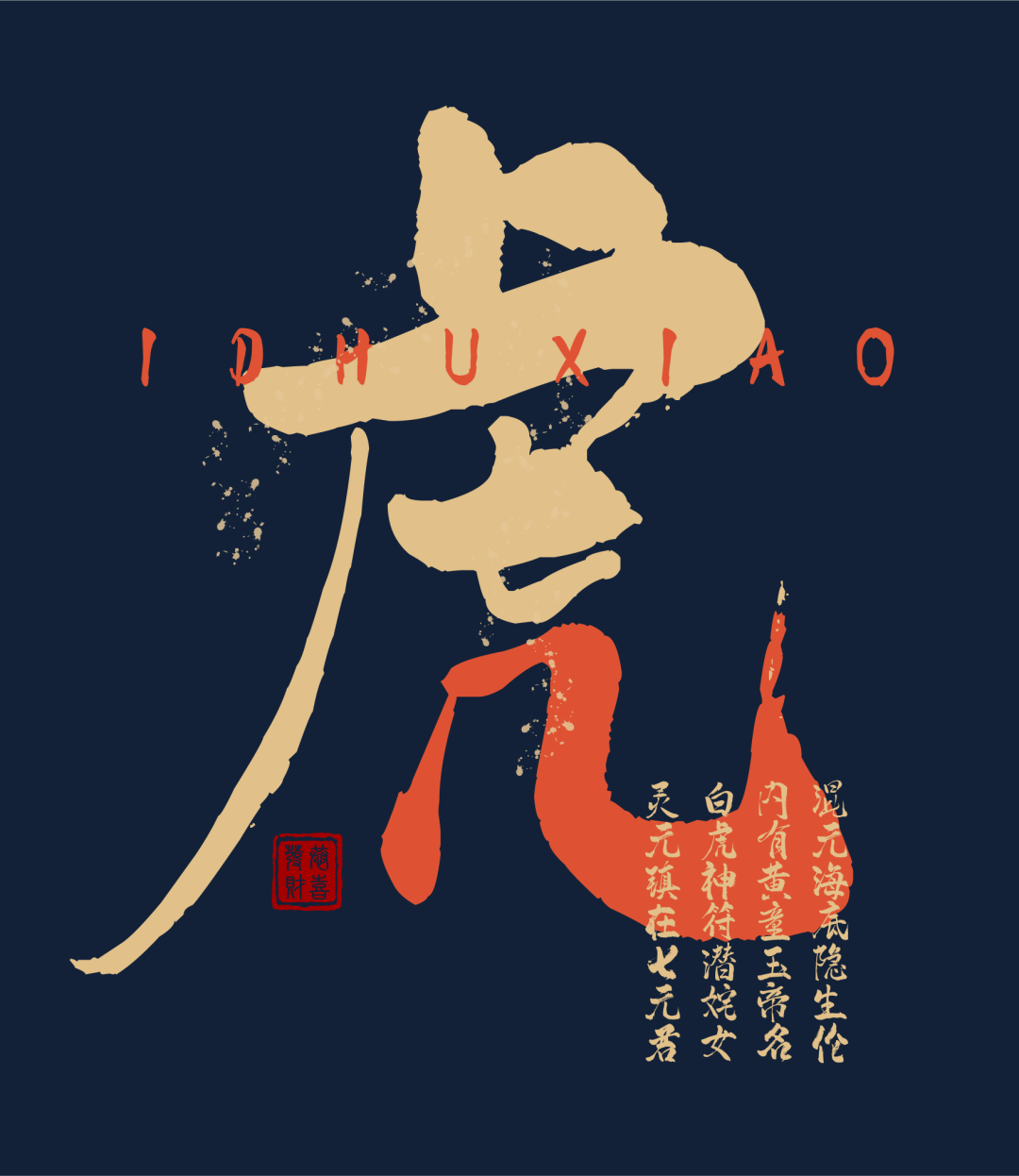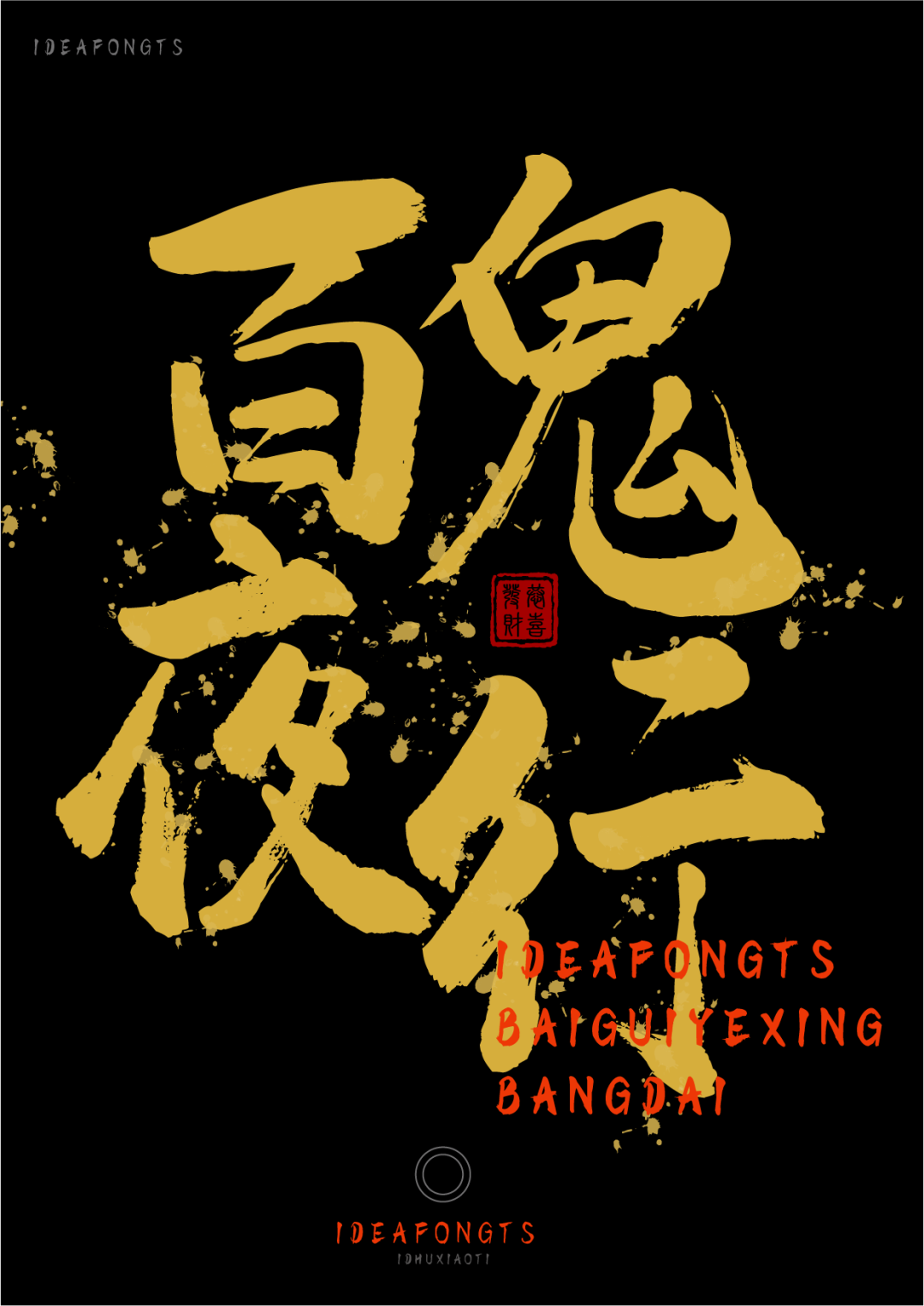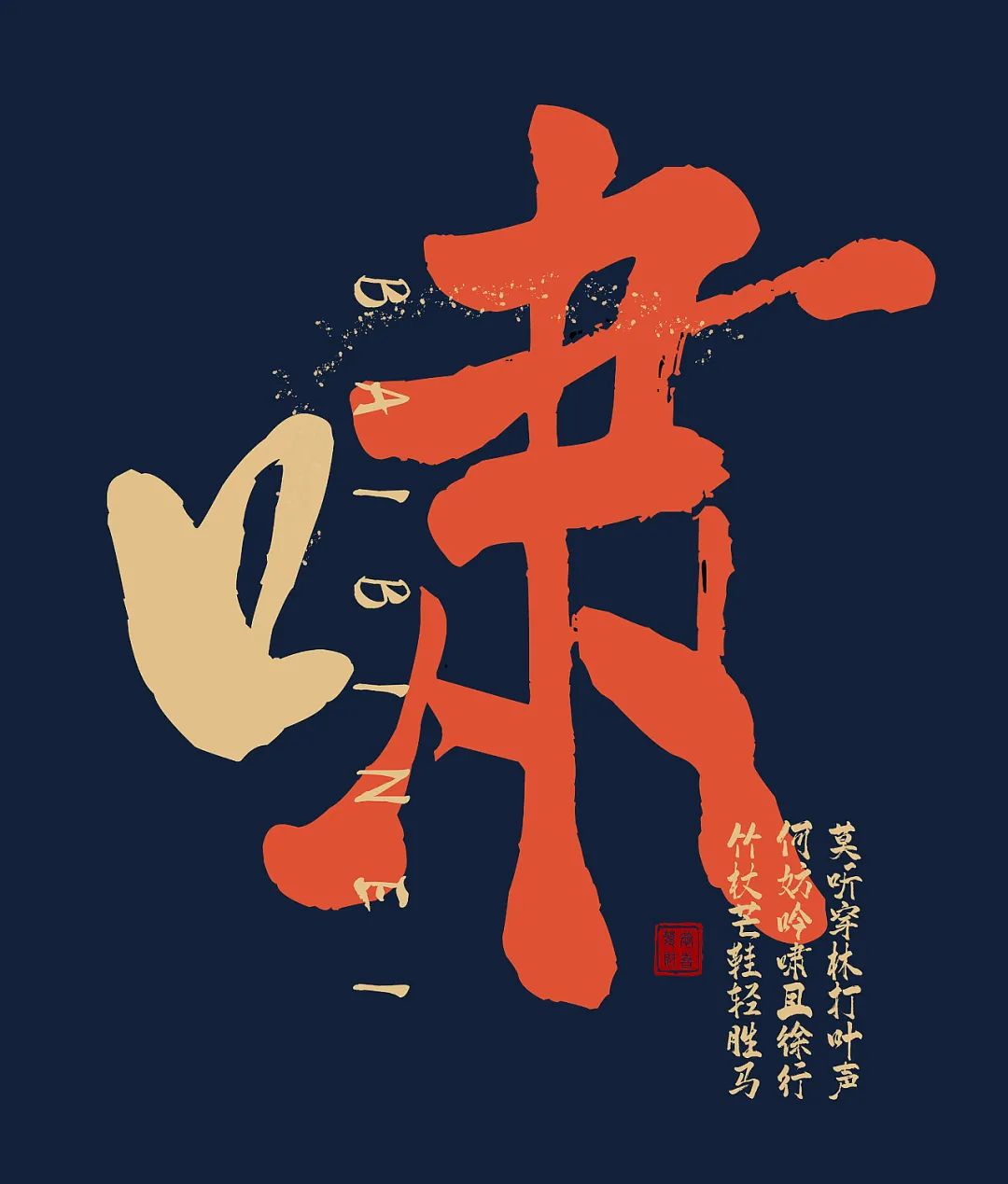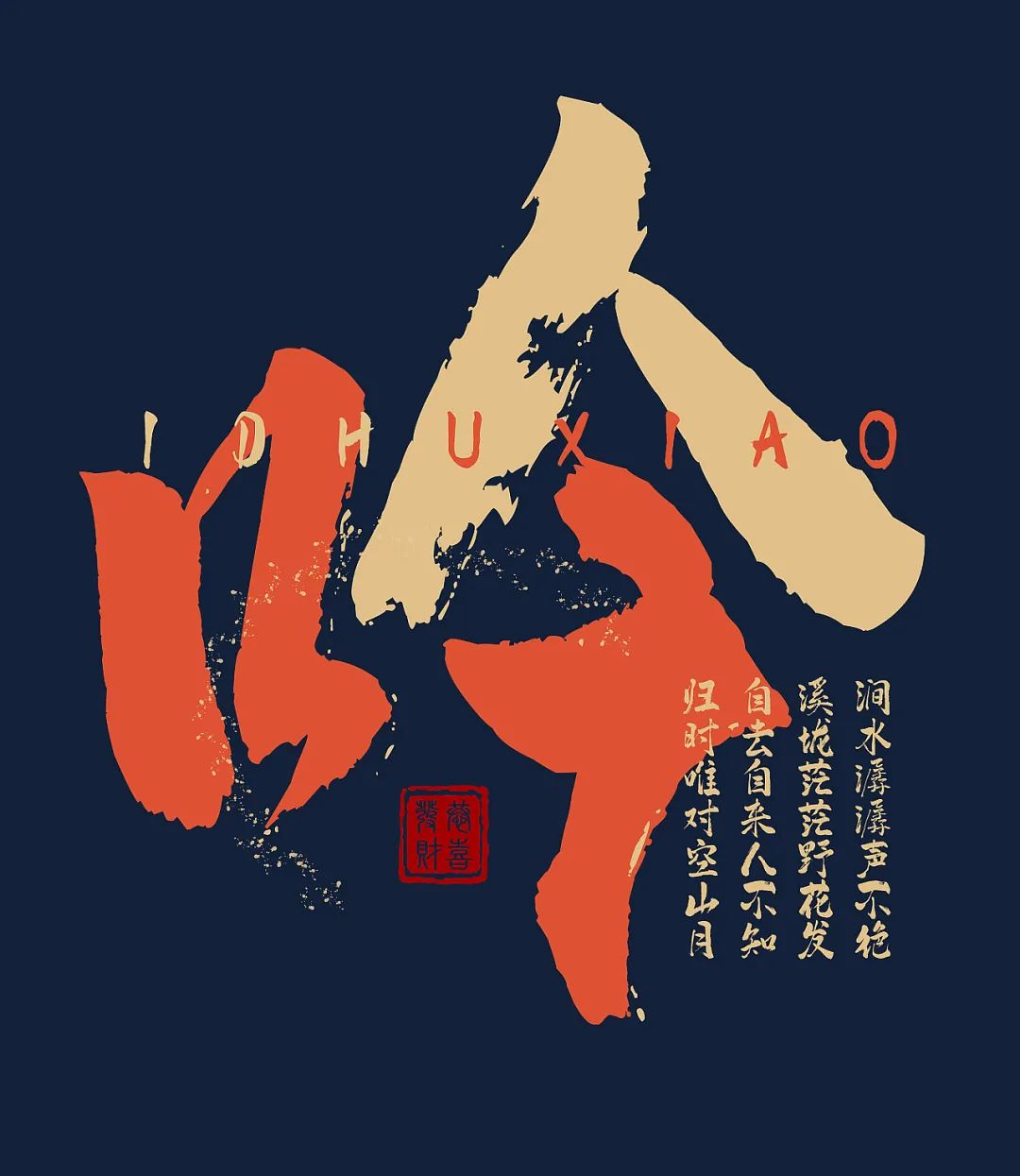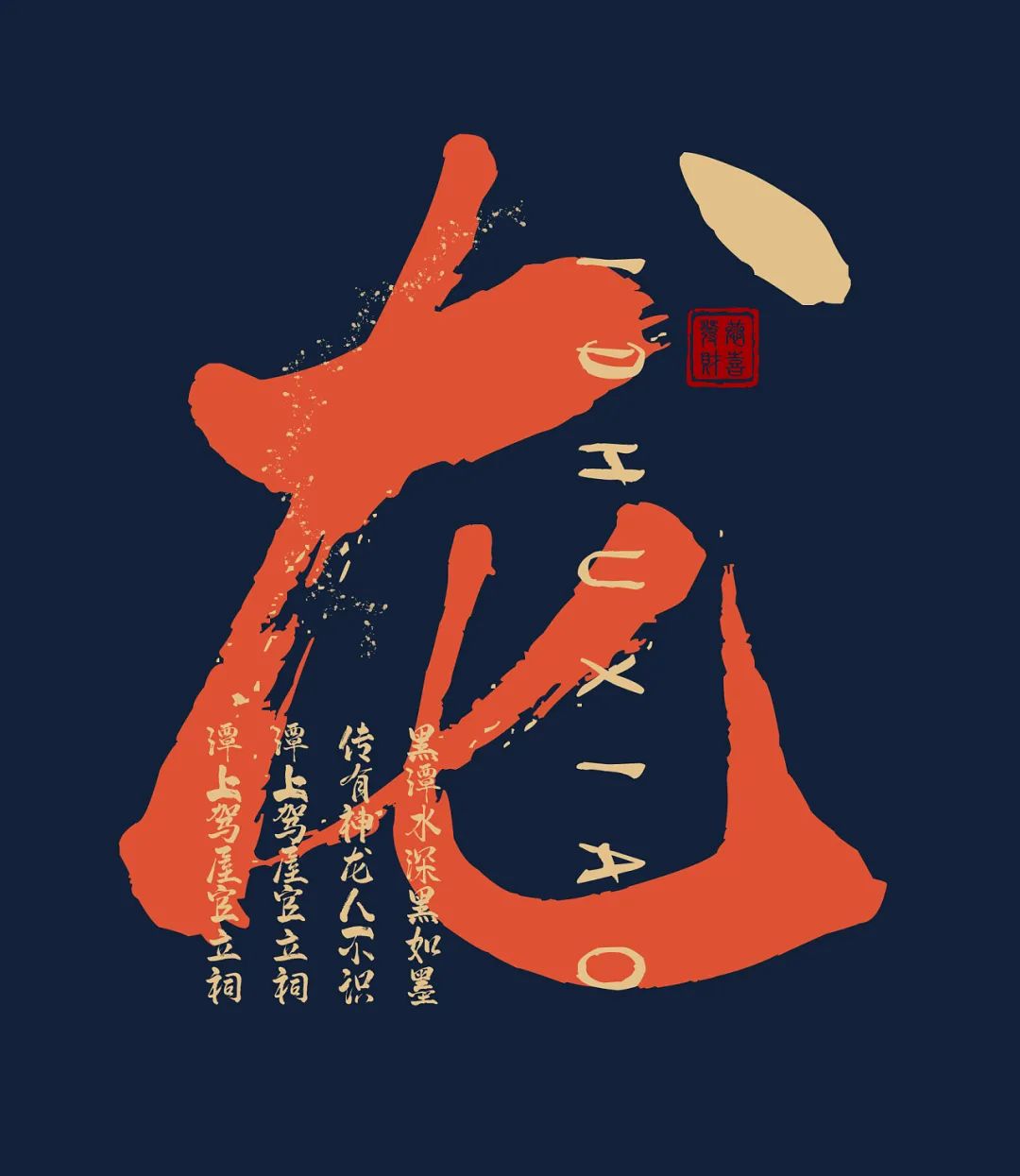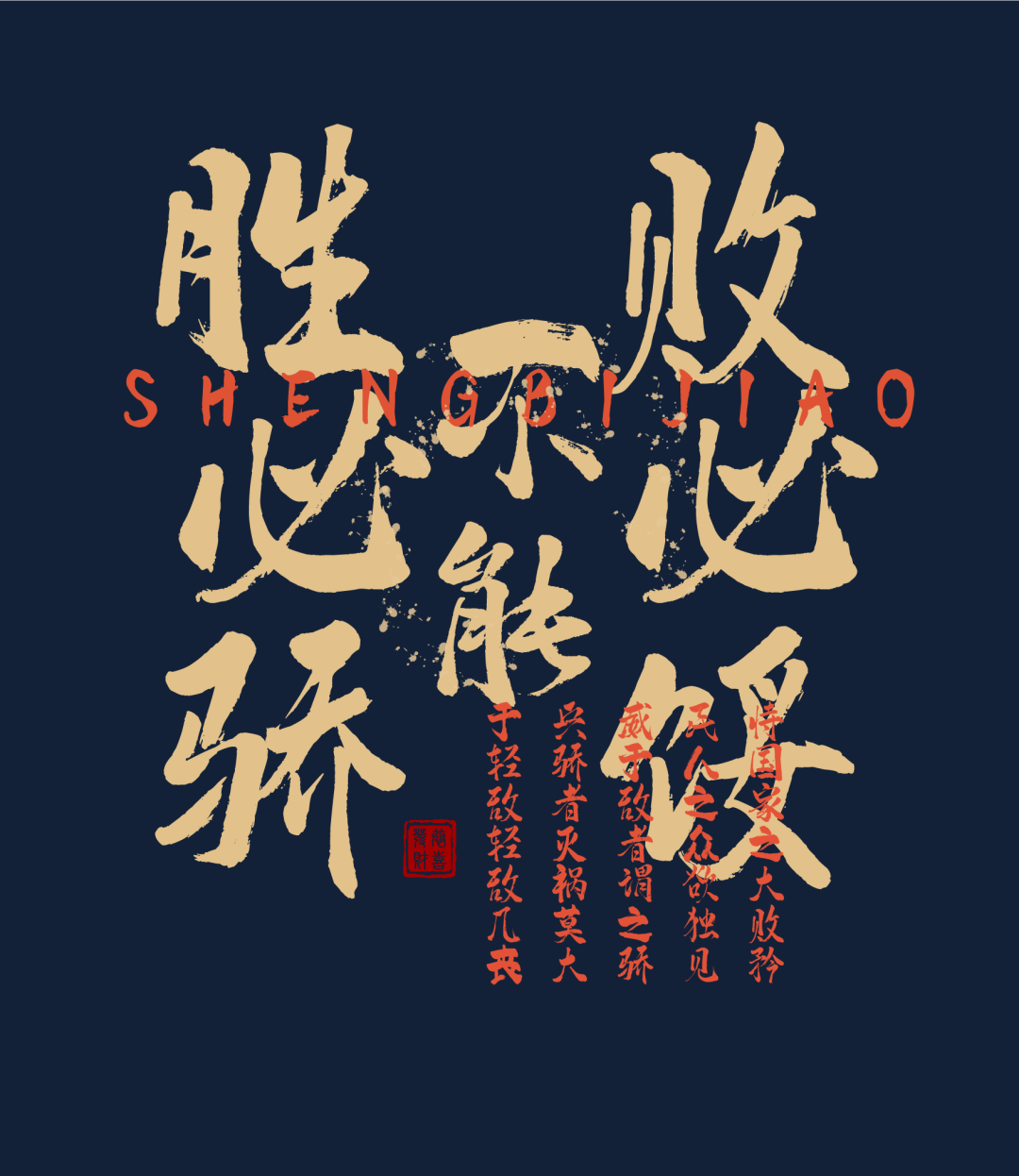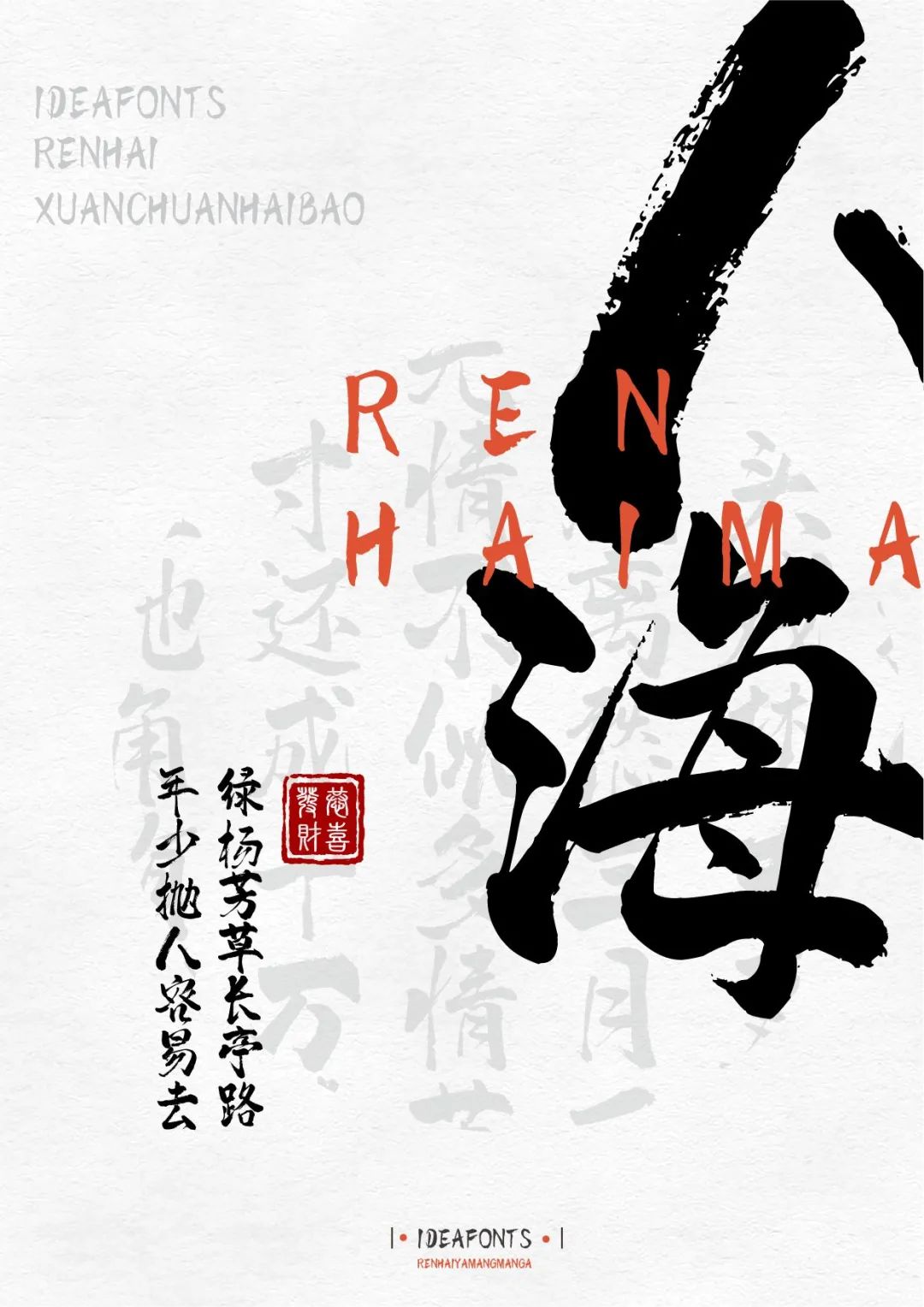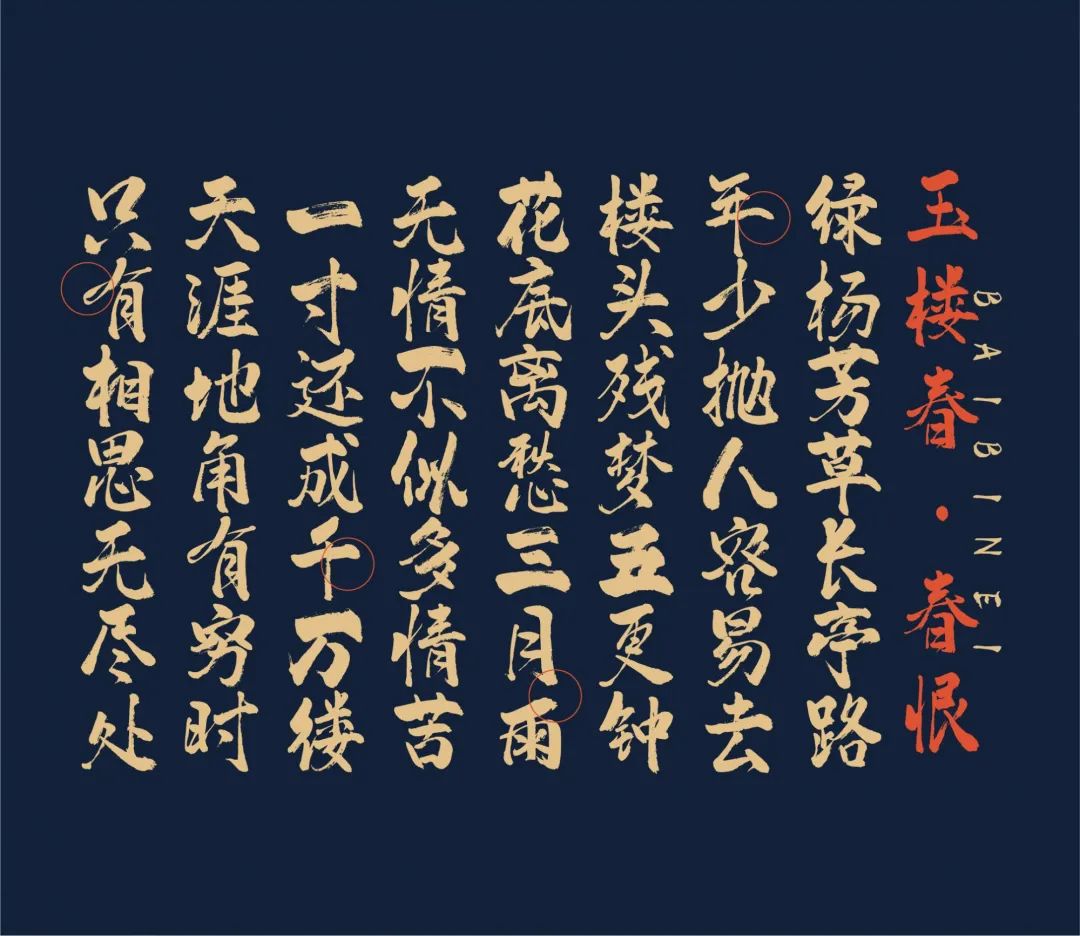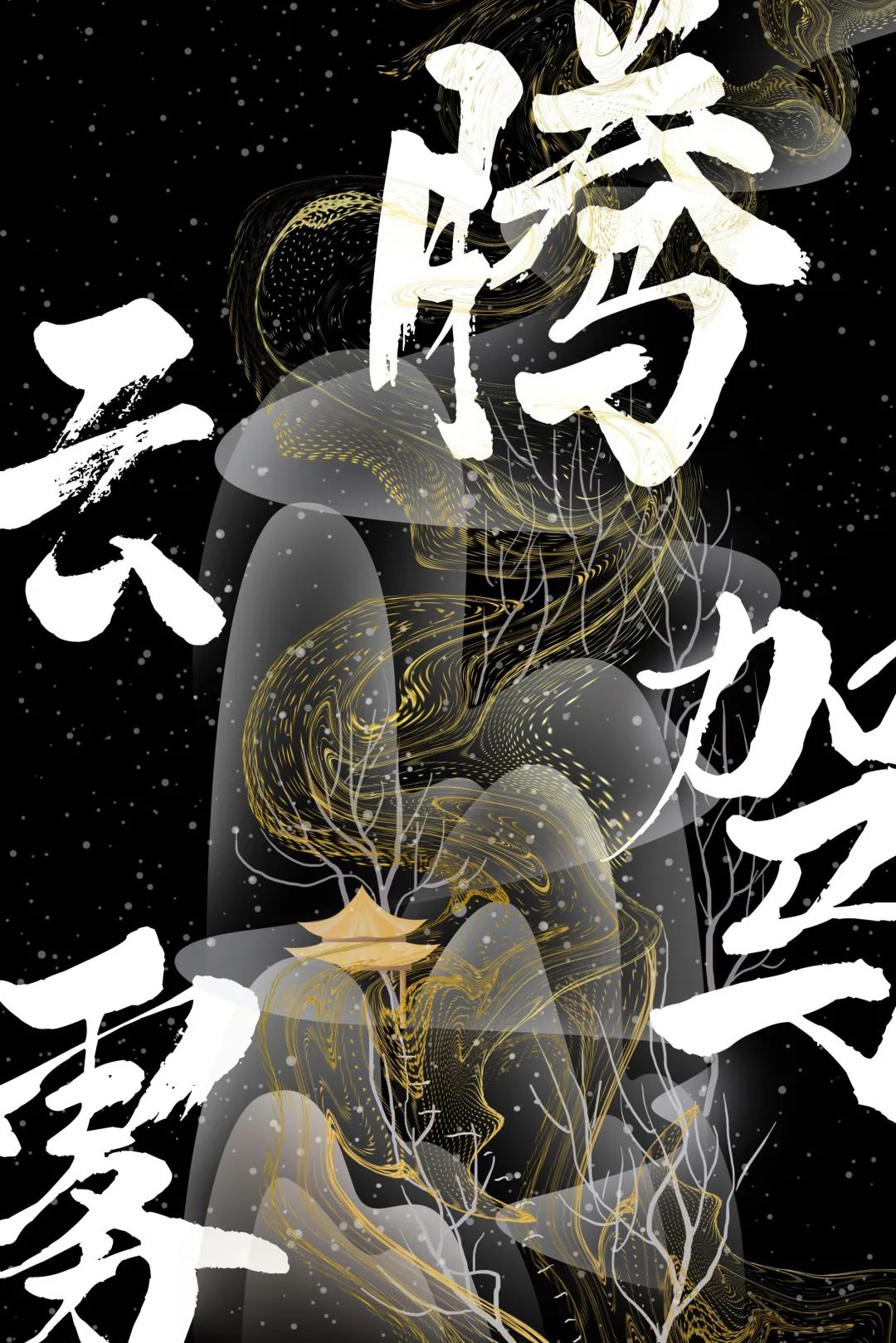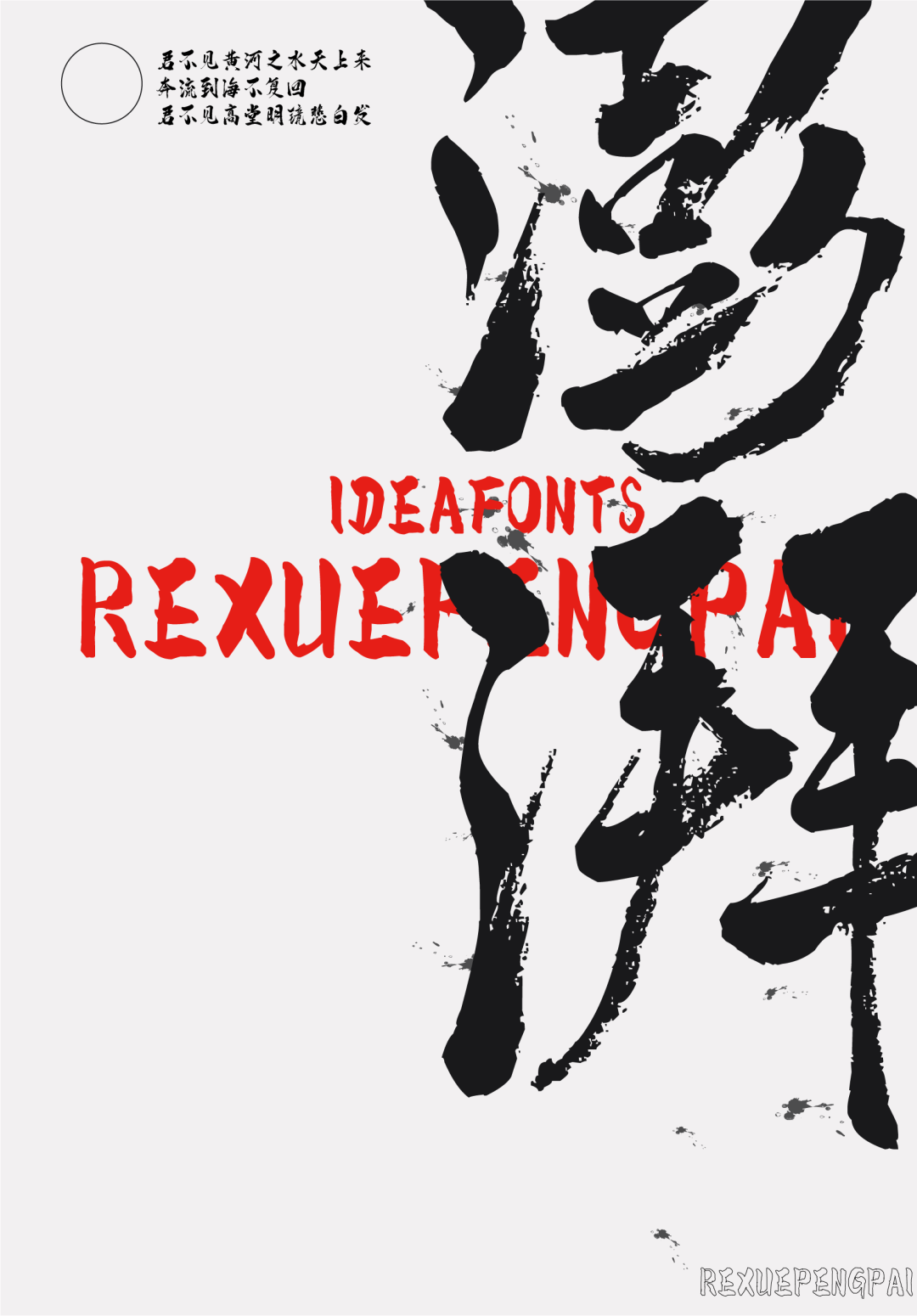
什么样的书写体,能让你瞬间脱颖而出?
其中最引人注目的,就是几款个性书写体,毕竟市场上需求多多,也符合当下年轻人的态度,比如气场两米八的点字虎啸体。
它还有另一个兄弟款——点字腾凌体,非常有武侠的感觉有木有?
整体排版,能看到字里行间的“侠”气!
用做标题设计,有一种油然而生的历史感。
当然除了这两款字,会员商用中还有点字逸致体(繁体)、演示镇魂行楷、演示新手书、默陌狂飞侠客体……